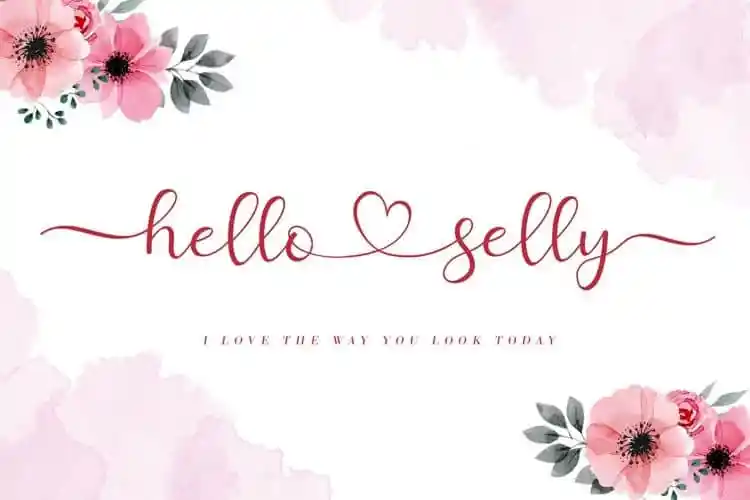
Hello Selly Calligraphy Font – Download Grátis
Descubra a magia do Hello Selly Calligraphy Font em sua próxima projeto criativo. Uma fonte script fresca e moderna, inspirada na escrita à mão com caracteres decorativos e uma linha que dança sobre as linhas de base. Ideal para convites artesanais, cartões de parabéns, materiais de marca, cartões de visita, citações e painéis. Este é um fonte elegante e fluido criado pela AEN Creative Studio. Perfeita para quem busca uma pitada contemporânea em estilos clássicos. Com linhas suaves, glifos belos e alternativas surpreendentes, essa fonte mantém sua influência calligrafica enquanto ganha um ar de modernidade e frescura. Experimente Hello Selly e deixe seus projetos brilharem ainda mais!